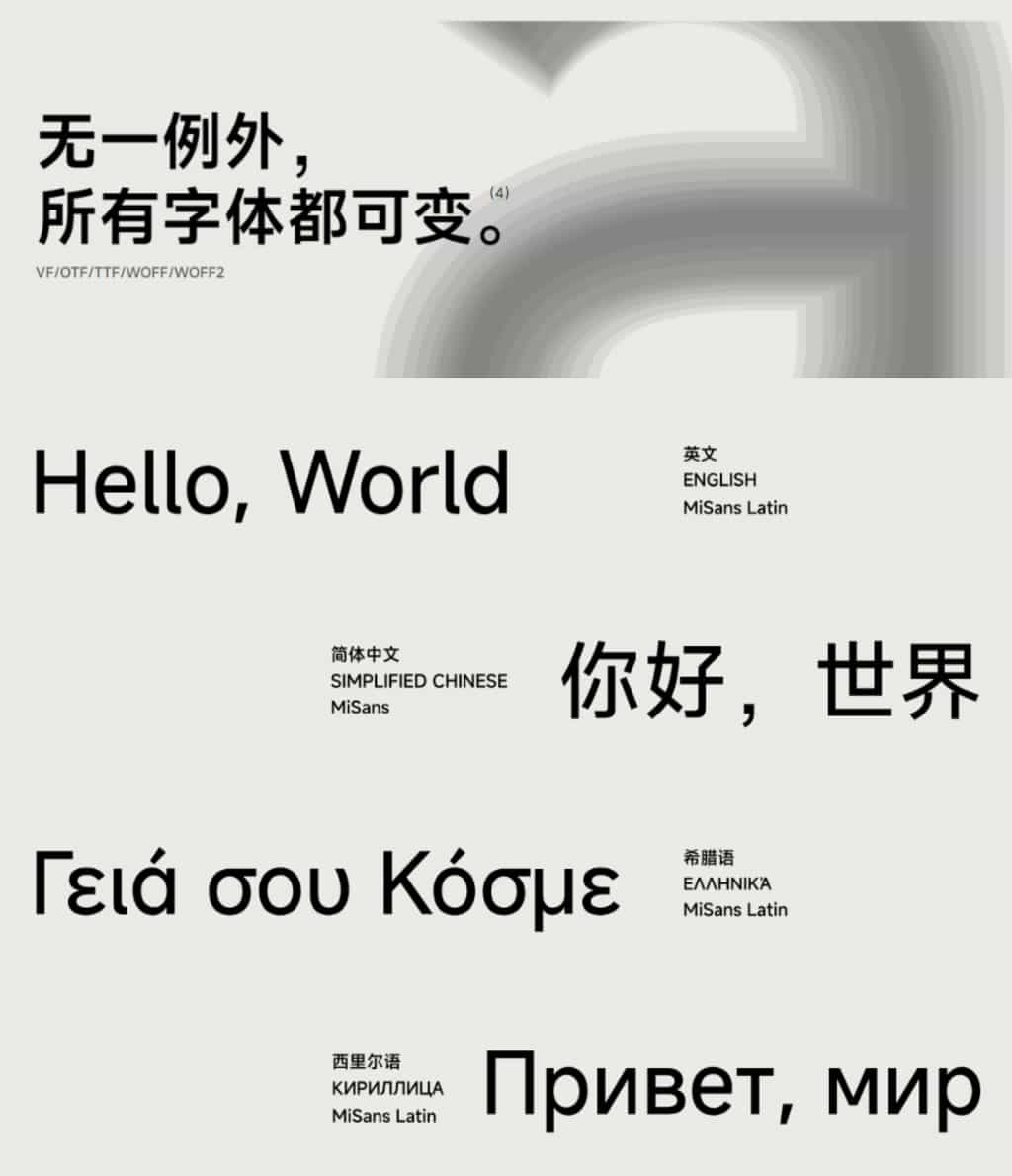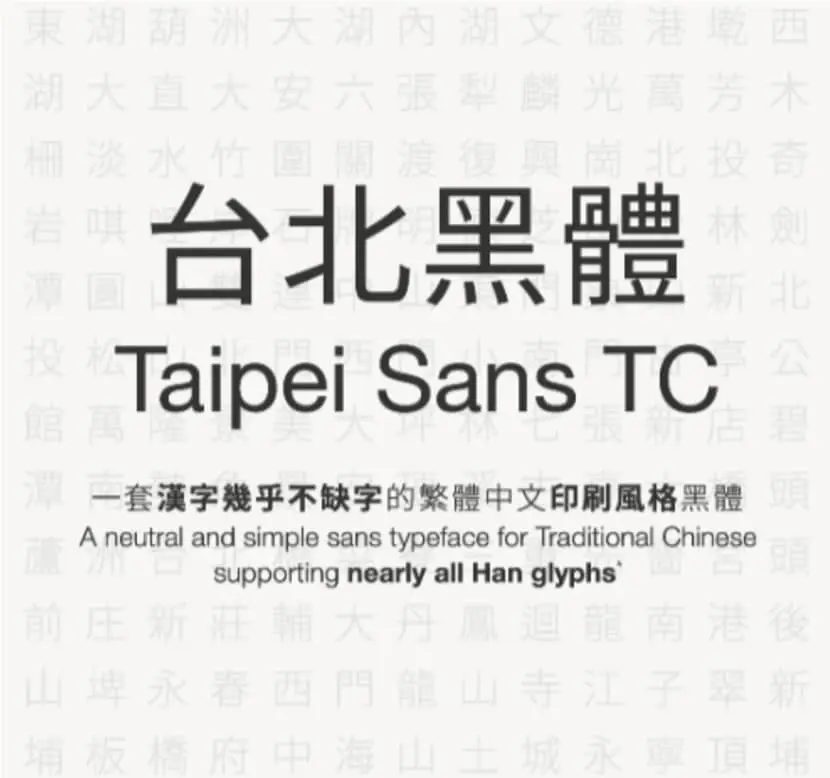
台北黑體:適合文字編排、平面設計、影音字幕使用的繁體中文免費字型台北黑體是基於思源黑體進行調整的黑體字型,由「翰字鑄造」(JT Foundry)著手改良,讓思源黑體更適於印刷使用。翰字鑄造提出時下免費的繁體中文字型大多符合台灣及香港的教育部門標準,不盡然適合印刷。台北黑體在以思源黑體作為基礎下改善一些部件寫法,維持漢字的對稱之美,並持續讓字符也保有漢字結構的平穩和剛直,當然更重要的是讓印刷用字型維持印刷體的樣貌。免費字型中文字型2023/07/17閱讀全文
嘉市體:嘉義市政府推出的中文字型 Chiayi City Font,可商業使用嘉市體字型不但免費且還是可以商業使用的字體,任何人都可以從嘉義市政府網站下載使用。目前,嘉市體已經在市政府內指示牌、公共場所指標、網站等處,持續推廣。嘉義市政府希望透過這款字體,把嘉義的特色和魅力推廣至國際,增加對嘉義的認同感和吸引力。免費字型中文字型2023/06/13閱讀全文
小米 MiSans 免費中文字型 10種字重支援繁體可商業用途根據說明,MiSans 字型共收錄了29,093個字元,並支援多國語言,包含繁體中文字體。MiSans 字型的特色之一是提供多種 OpenType 功能,可以根據特定需求選擇不同型態的字元,例如某些標點符號會根據周圍字母的型態自動調整到適合的位置。想要下載 MiSans 字型,只需前往「小米社區」頁面,找到 MiSans 字體的下載鏈結,即可順利獲得完整套的 MiSans 字型。這套字型包含十種字重,層次清晰,並且開放給所有人免費使用,同時也適用於商業用途而不受任何限制。免費字型中文字型2023/06/08閱讀全文
隨峰體:免費中文手寫字型下載,開放原始碼可用於商業用途「隨峰體」這款字型有硬筆字的風格,特色是充滿了生活氣息和個性,雖說有時候會有些歪斜或不規則,但卻又不失美感和可讀性。隨峰體適合用於各種場合,無論是在網頁、Youtube、Facebook、影片、廣告、印刷等中個人或商業,均可以免費使用。免費字型中文字型2023/06/04閱讀全文
全字庫「說文解字 True Type 字型」免費下載使用依據說明「說文解字 True Type 字型」的出處來自許慎著作《說文解字》一書,該書是中國第一部有系統性的分析漢字字形和考究字源的字書。原書十四篇,敘目一篇,正文以小篆為主。收 9353字,古文、籀文等異體同文1163字,解釋十三萬餘字。但是說文解字原文與現行之 Unicode 編碼並無一完整的對應。因此無法將所有的字形收錄於說文解字 True Type 字型檔。目前收錄有 6721個字。所以真要應用小篆,就需要有缺字的因應對策。免費字型中文字型2023/06/02閱讀全文
教育部標準楷書、隸書及宋體字體免費下載,適用於 Windows 和 Mac「教育部語文成果網」推出了「楷書」、「宋體」及「隸書」國字標準字體字形檔,供 Windows 及 Mac 作業系統安裝使用,其中,以楷書收錄國字數為 13,076字為最多,3套字形著作權均採創用 CC「姓名標示-禁止改作 3.0 臺灣版」授權,有興趣的用戶,可多加利用。免費字型中文字型2023/06/02閱讀全文